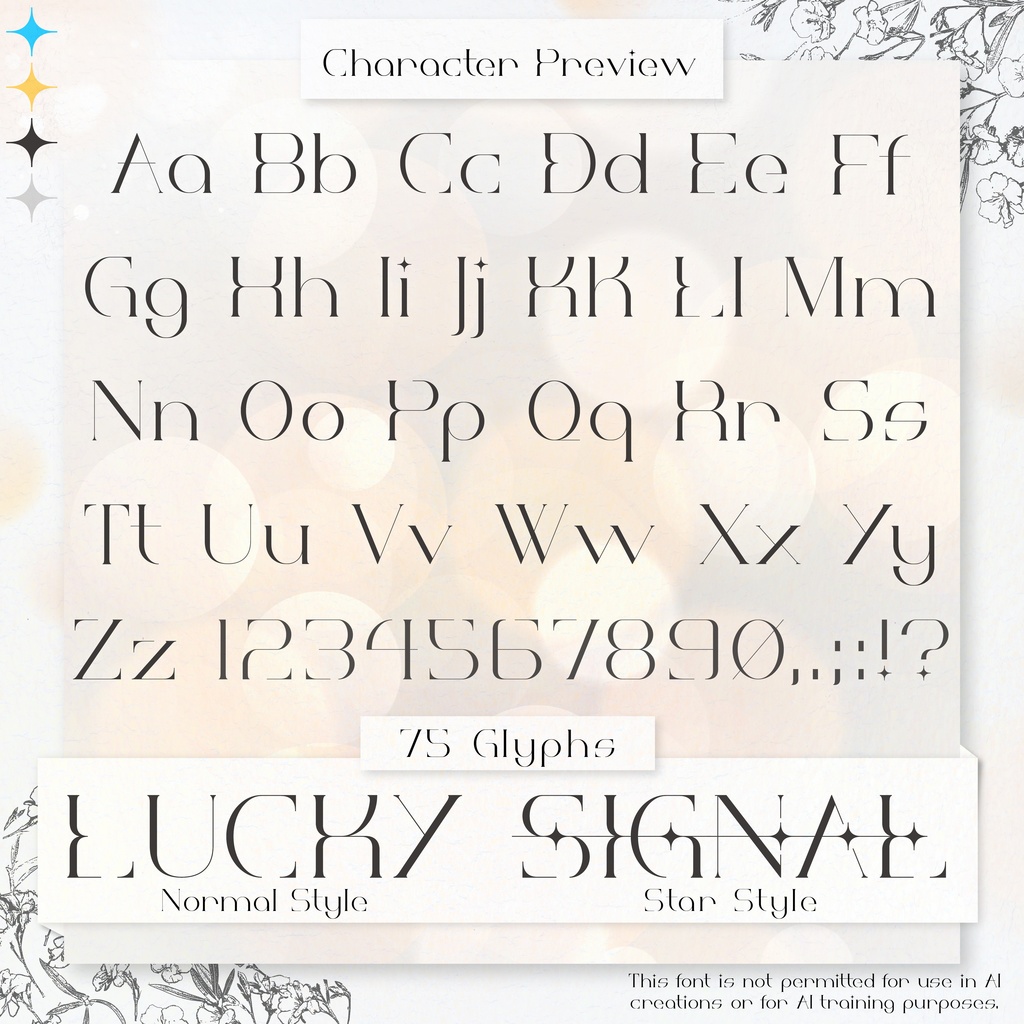
【無料DL企画開催中】✦ Lucky Signal ✦【セリフフォント】
📢デザイン📢
繊細で一部省略された筆画が軽やかで優雅な印象を与えます。Star版ではすべての字母がつながり、まるで星座がつながるようなデザインになっています。 漫画の中で優雅なキャラクターのクローズアップや同人誌の表紙デザインのようなデザインで、華やかな印象を与えます。